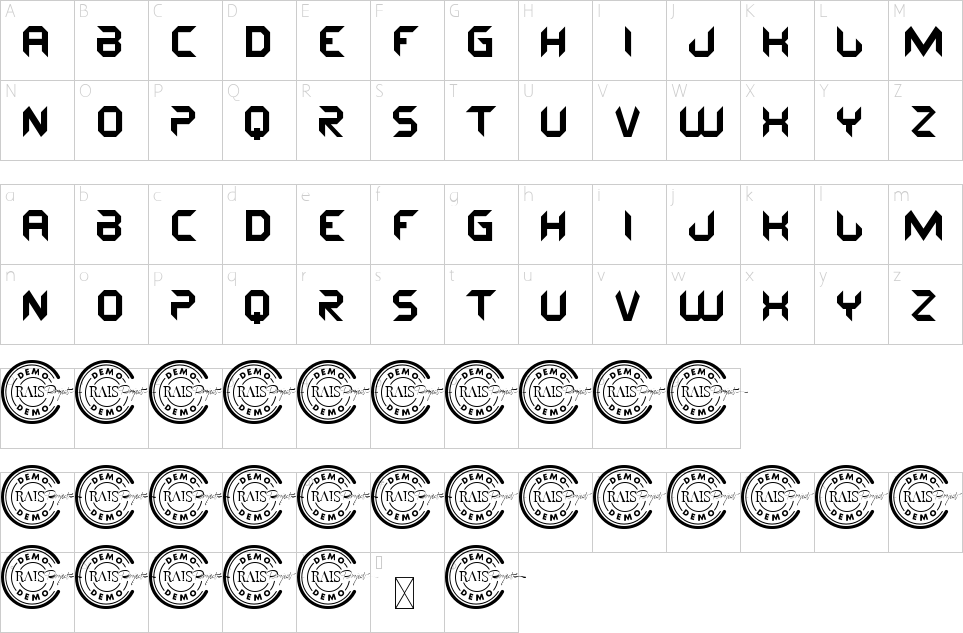
Gunrace Font – Download Grátis
Aqui está uma descrição em português para a página de download da font ‘Gunrace Font’, seguindo as orientações fornecidas: Aproveite essa oportunidade para decorar seu próximo projeto visual com a elegante e moderna ‘Gunrace Font’. Desenhada pelo designer desconhecido, esta fonte gratuita está disponível tanto para Windows quanto para Mac. A sua simplicidade sofisticada e clareza legível tornam-na uma escolha ideal para designers gráficos que procuram um elemento único em seus projetos. Com seu design limpo e minimalista, a ‘Gunrace Font’ adiciona um toque de modernidade aos textos mais simples. E o melhor é que você pode agora ter essa fonte à sua disposição sem precisar pagar uma centinha sequer – graças ao seu status gratuito. Não deixe essa oportunidade passar e transforme seus projetos em algo realmente especial. Esta font foi baixada 3,349 vezes por designers apaixonados pelo design gráfico, demonstrando a sua qualidade e conveniência de uso. Seja para contratos empresariais ou simples designs pessoais, a ‘Gunrace Font’ traz um toque inconfundível ao seu trabalho. Tente agora e descubra o poder desta fonte gratuita.